29 款冰冷设计的最佳冬季字体
下面,我们列出了 29 种最酷的字体,它们非常适合节日贺卡、圣诞展示和所有其他冬季主题设计。
此列表中的所有冬季字体均由专业人士设计并由我们手工挑选。 它们都唤起了寒冷的季节,让人想起在明火旁烤着雪、冰和栗子的画面。
29 种最佳冬季字体
1.冬天——我们的首选
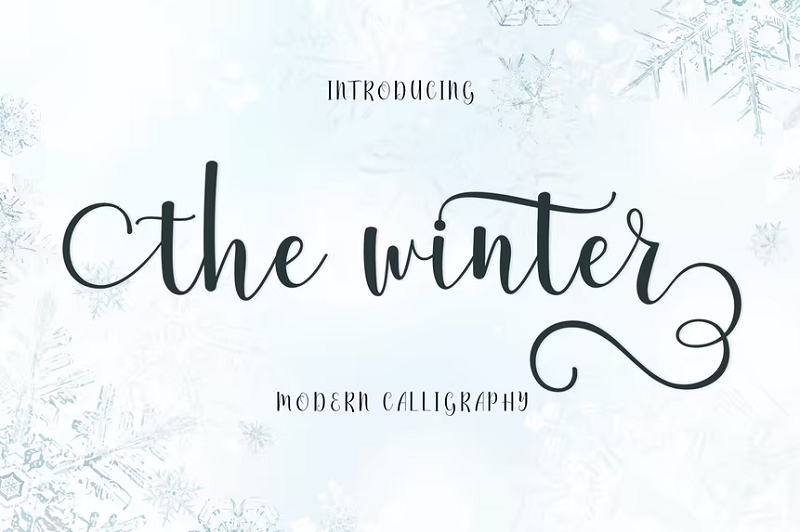
我们的首选是 The Winter,这是一种时尚、低调的书法字体。 它是 Envato Elements 上最受欢迎的冬季字体之一,带有 300 多个字形,包括花体字、上下文替代字和风格集。
为什么它是我们的首选
这是我们总体上最喜欢的冬季字体的主要原因是因为它的多功能性和品味。 手写字体优雅而现代,带有长尾巴和花饰等装饰,在不影响可读性的情况下增加了个性。
它简单干净,不像许多其他冬季主题字体那样显得过于夸张或俗气,因此它适用于许多不同的设计(尤其是节日贺卡)。
2.冬梦
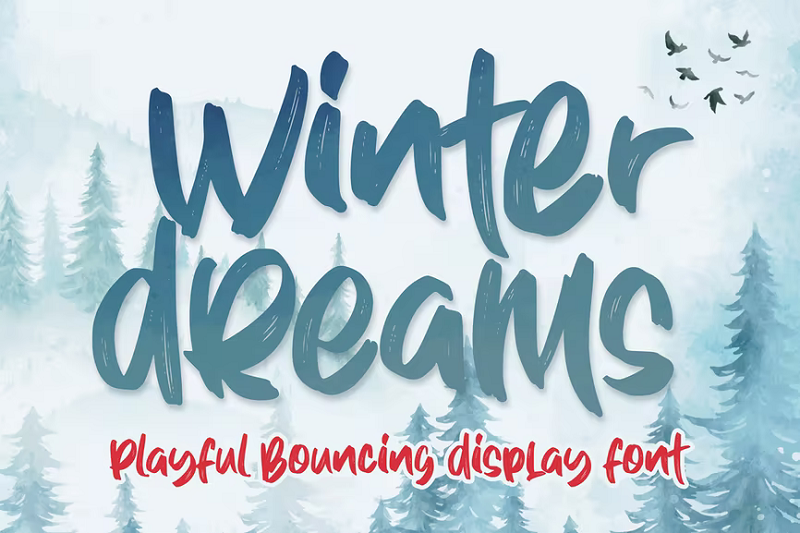
接下来,我们有 Fige 的 Winter Dreams。 这是一种俏皮、有弹性的显示字体,具有自然的笔触和寒冷的设计。 它不像我们的首选那样重视自己,也没有任何夸张的装饰,但它既有趣又时尚。
3.冬季王国
Winter Kingdom 是一种全大写的冬季字体,使用粗大的正楷字母。 它非常有趣、卡通化且外观友好,因此我可以看到它在面向儿童的设计中运行良好,例如在冬季主题的儿童书籍封面或手机游戏中。
4.雪花字体
Snowy 是我们遇到的最独特的冬季字体之一。 它使用带有装饰性花卉装饰的粗体大写字母和雪花等复杂细节,使其看起来更加神奇 - 所以它非常适合圣诞节设计
Snowy 使用新的 OpenType SVG 字体格式(即彩色字体)。 与传统格式相比,这种格式使设计师能够真正发挥创意并为字母添加更多细节。
5.圣诞故事
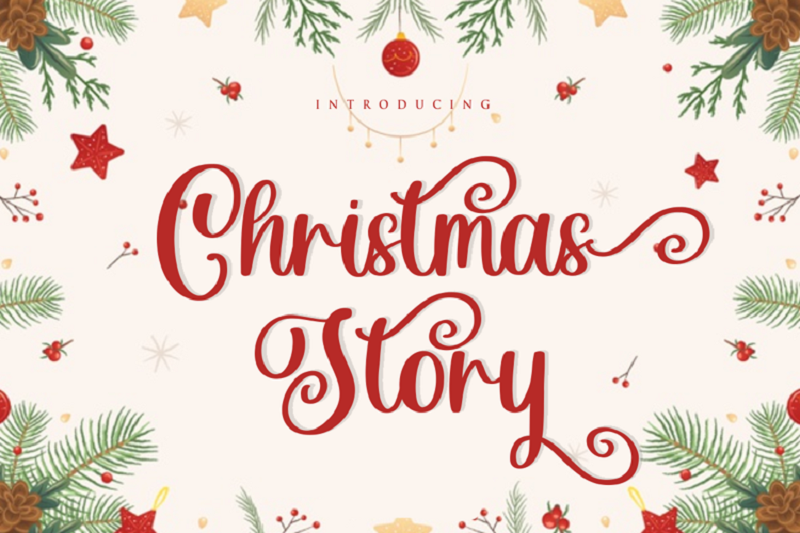
如果您正在从事以圣诞节为主题的设计项目,请查看圣诞节故事。 这种节日字体采用现代手写设计,带有开头和结尾的花体。 它简单、优雅,而且——最重要的是——免费!
6.雪色字体
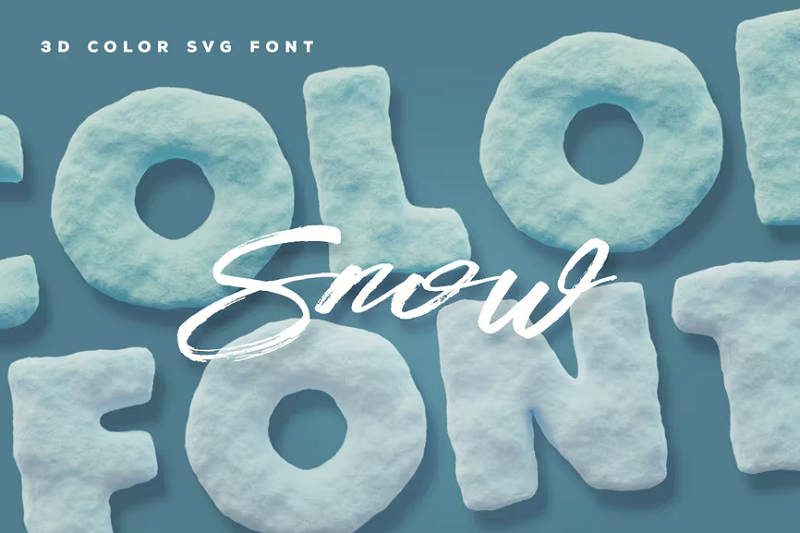
Snow 是另一种 SVG OpenType/Color 字体,仅适用于现代版本的 Photoshop 和 Illustrator。 它有两个版本:冬季主题和雪地主题。 两者都利用了很酷的 3D 效果,使它们跳出页面。 它们非常详细,粗糙的纹理使它们看起来好像是从冰雪块中切割出来的。
7.在雪字体下
Under The Snow 是一种简单的、以雪为灵感的分层字体。 下载包附带免费字体版本:Regular、Style 01、Style 01 inner 和 Style 02。每种字体的设计略有不同。 Style 02 是我们最喜欢的,它的设计看起来就像字母从天上掉下来时慢慢地被雪填满。 您可以将分层的内部字体添加到任何其他字体以创建很酷的效果。
8. Fronzy
Fronzy 是另一种有趣的冬季字体。 这是一种粗犷的字体,带有粗大的字体和波浪形的笔触,使它看起来有点像云。 它具有冰冷的美感,适用于各种冬季设计。 它还带有大写和小写字母、符号、标点符号、数字、替代和多语言支持。
9.冬季苏打水
Winter Soda 是一种现代的手写冬季字体,具有自然的触感。 它既女性化又优雅,适用于贺卡、徽标、书籍封面和文具。
10.圣诞节时间
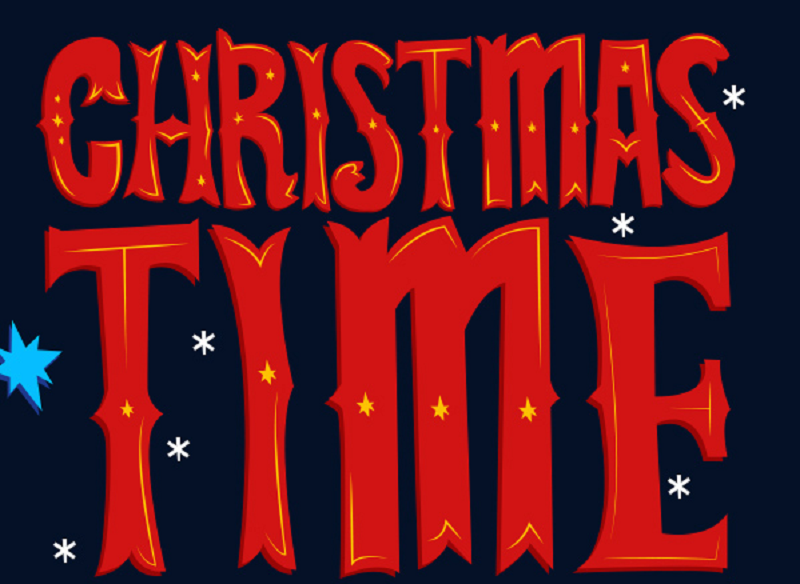
这是您在任何地方都能找到的另一种最好的圣诞字体。 Christmas Time 是 Lukasz KuIakowski 的免费字体。 设计师显然在字体上付出了很多努力,并在每个笔划中添加了复杂的细节,如星星,使其看起来更加喜庆。
11.冰山
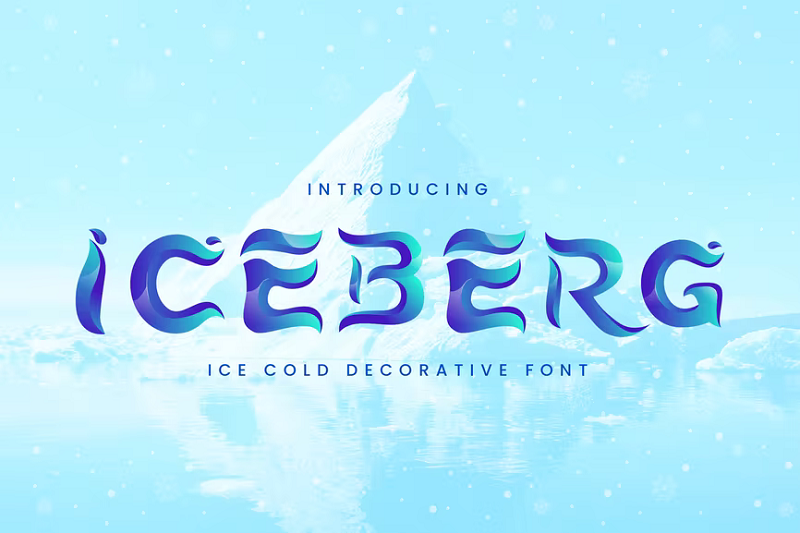
Iceberg 是一款来自设计师 Naulicrea 的冰冷装饰显示字体。 波浪形的笔触使这种字体独一无二,与此列表中的任何其他字体都不同。 它采用 TTF 和 WOFF 格式,包括 AZ 字母、数字和标点符号,以及 26 个免费的详细冰字母矢量图像,您可以在徽标中使用它们。
12.可爱的雪人
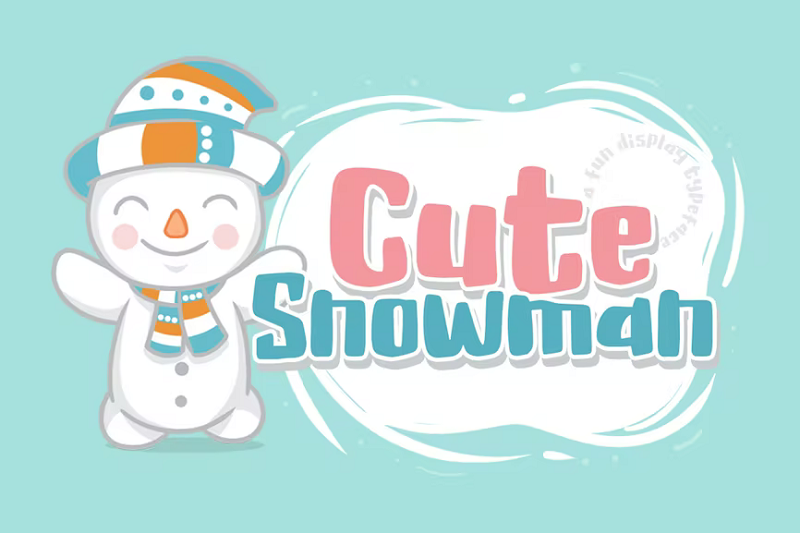
顾名思义,Cute Snowman 是一种超级可爱的显示字体,非常适合俏皮和乐观的设计。 它在儿童产品、标志、T 恤、贺卡和海报上看起来很棒。 下载包包括 TTF 和 OTF 字体文件,以及可爱的雪人矢量图像。
13.长子
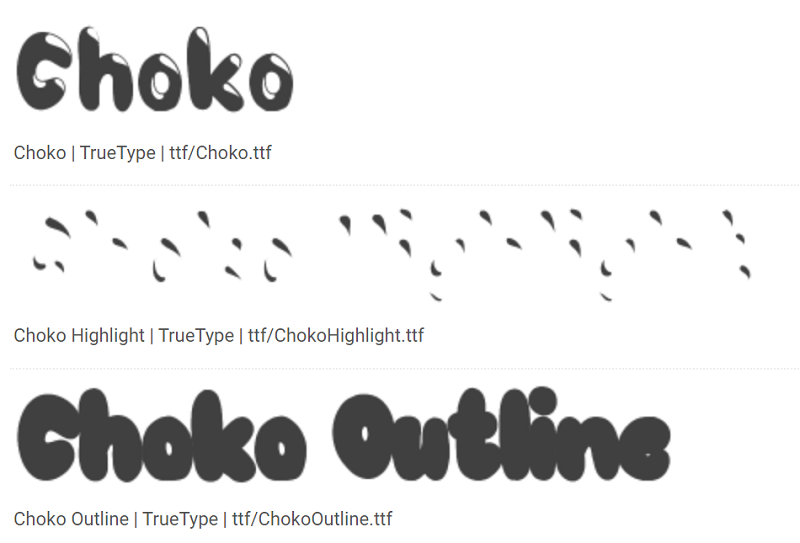
Choko 是设计师 Mans Greback 的另一款雪白字体。 它具有圆形、雪顶字体,并有多种样式,包括 Choko Outline、Choko Plain、Choko Highlights 和 Choko Shadow。 您可以将这些不同的版本叠加在一起以创建多色图层效果。
14. Winter Bells 字体
接下来,我们有 Winter Bells,这是 Attype-Studio 的圣诞字体。 这种字体最酷的地方在于它带有铃铛的dingbat字符,这使它看起来像每个字形上都挂着小玩意。 它非常适合圣诞节产品包装、品牌和其他节日设计。
15.冬季乐园
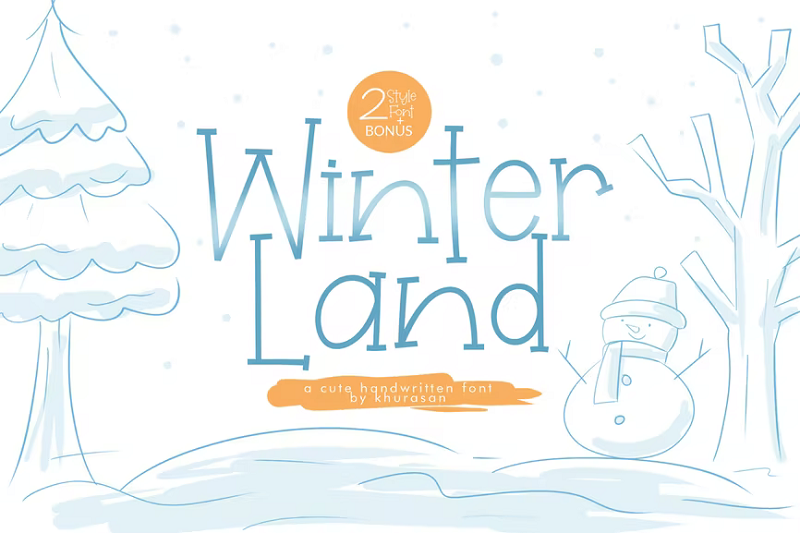
WinterLand 是一种简单的衬线字体,有两种样式:常规字体和倾斜字体。 它相当轻,适用于海报、杂志、横幅和大型展示艺术品。 它采用 TTF 和 OTF 格式,包括 AZ、az 和 1-9 字形,以及标点符号和多语言支持。
16.东南亚
Southea 是 Attype-Studio 出品的单线显示字体。 它有两种变体:常规样式和显示样式。 展示风格的设计看起来好像雪从字母底部滴落,因此非常适合冬季和圣诞节主题设计。
17.最酷的冰冷字体
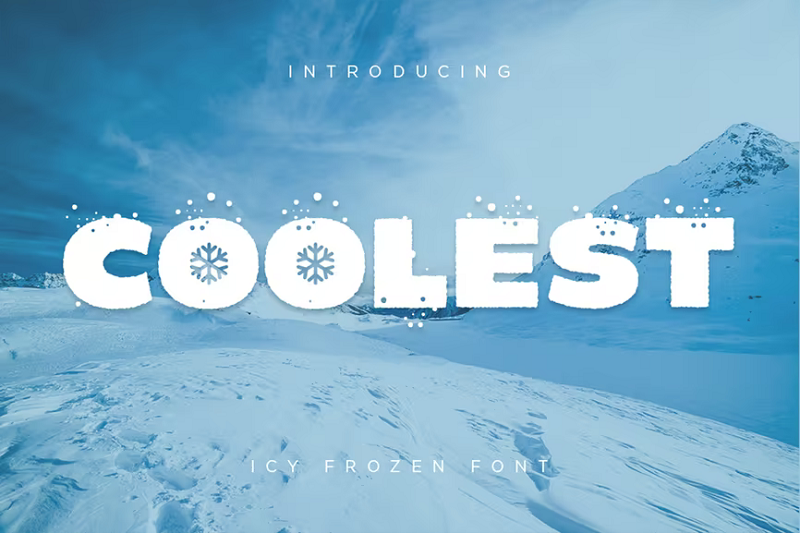
最酷的,由 Konstantinestudio 设计,是一种很有冲击力的字体。 它又大又粗,而且影响很大,因此非常适合真正需要文字突出的设计。 设计师从冬季中汲取灵感,并添加了雪花莲和雪花形状的柜台等冰冷细节。
18.冰河时代彩色字体
这是 Cruzine 在 Envato Elements 上的另一种超逼真的彩色字体。 这种字体看起来好像是用一块冰雕刻出来的。 它的细节令人难以置信,具有逼真的冰冷纹理(表面有裂缝)和斑驳的蓝色。
19.雪屋
如果您想保持简单,请尝试 Snowhouse。 Mans Greback 的这种免费草书字体优雅而优雅,带有漩涡状的雪顶笔触。 它非常适合圣诞贺卡。
20.冬季星期日
Winter Sunday 是 Envato Elements 上另一种有趣的冬季字体。 它使用厚厚的正楷,看起来好像被雪覆盖了。 它也有点俏皮和卡通,这使它成为儿童读物和其他有趣、友好的设计项目的绝佳选择。